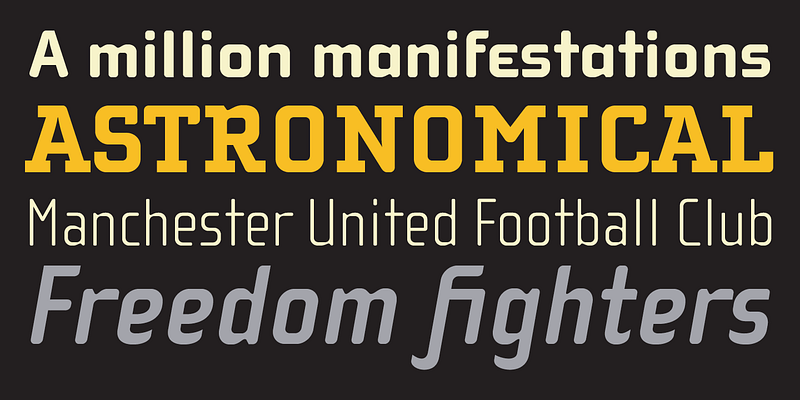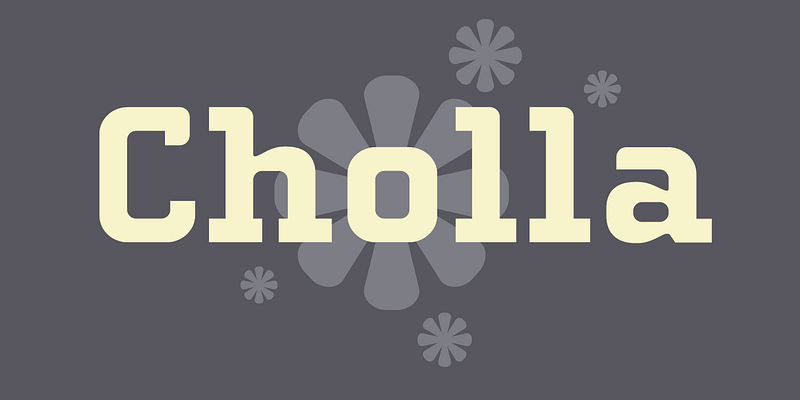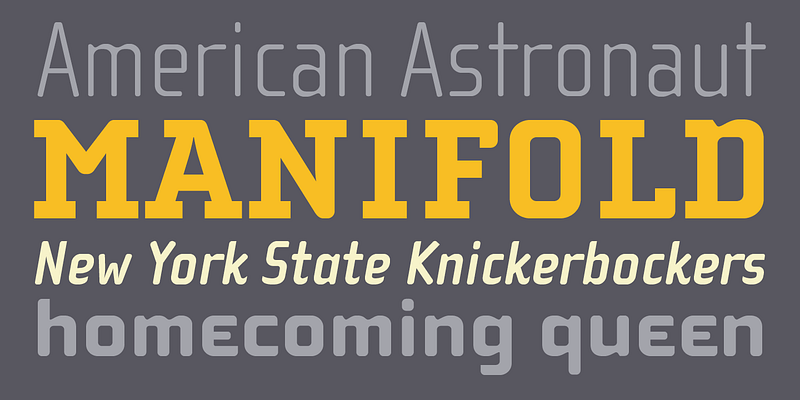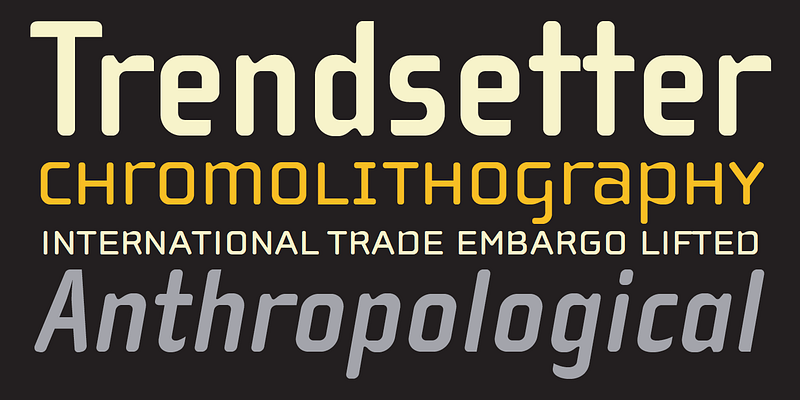
Cholla 書体ファミリーは 1998 ~ 99 年に Sibylle Hagmann にデザインされ、モハベ砂漠で彼女が出会ったサボテンにちなんで名付けられました。Cholla は元々カリフォルニア州パサデナにある Art Center College of Design で開発され、Denise Gonzales Crisp と同僚のデザイナーである Carla Figueroa が Hagmann と協力して、バリエーション豊かなフォントシリーズを作りました。学校の 9 学科に対応するために、バラエティがありつつ統一感のあるフォントが必要でした。1999/2000 Art Center カタログで初めて使用され、I.D. 誌で佳作に選ばれたほか、Eye No. 31 にも掲載されました。
Hagmann は元々、「まず、自分が気持ちよく作れる書体であり、目的を果たし、背後に明確なアイデアがあり、自分でも使いたくなる」書体にしようと考えていました。Hagmann は、文体的に「12 カットで微妙に異なる個性があり、別々のアイデアを適用しました。例えば、ボールドウェイトは単にレギュラーのウェイトを増やしたわけではなく、ボールドの字形には独特のディテールを入れています。すべてのウェイトが共有するものとディテールを統一するために必要なことは、例えば、小文字の「b」の左上や下部のボウルに見られるテーパーの曲線にあります」Gonzales は、「フォルムはクラシカルにも見えますが、長く息づくタイムリーなこの組み合わせになります。また、少なくとも最初の Cholla には相互接続で人間と機械が共に成長するハイブリッド性を含むフォルムが見られました。これらの概念は学校でデザインとアートを教えるのに適していると思います」と補足しました。